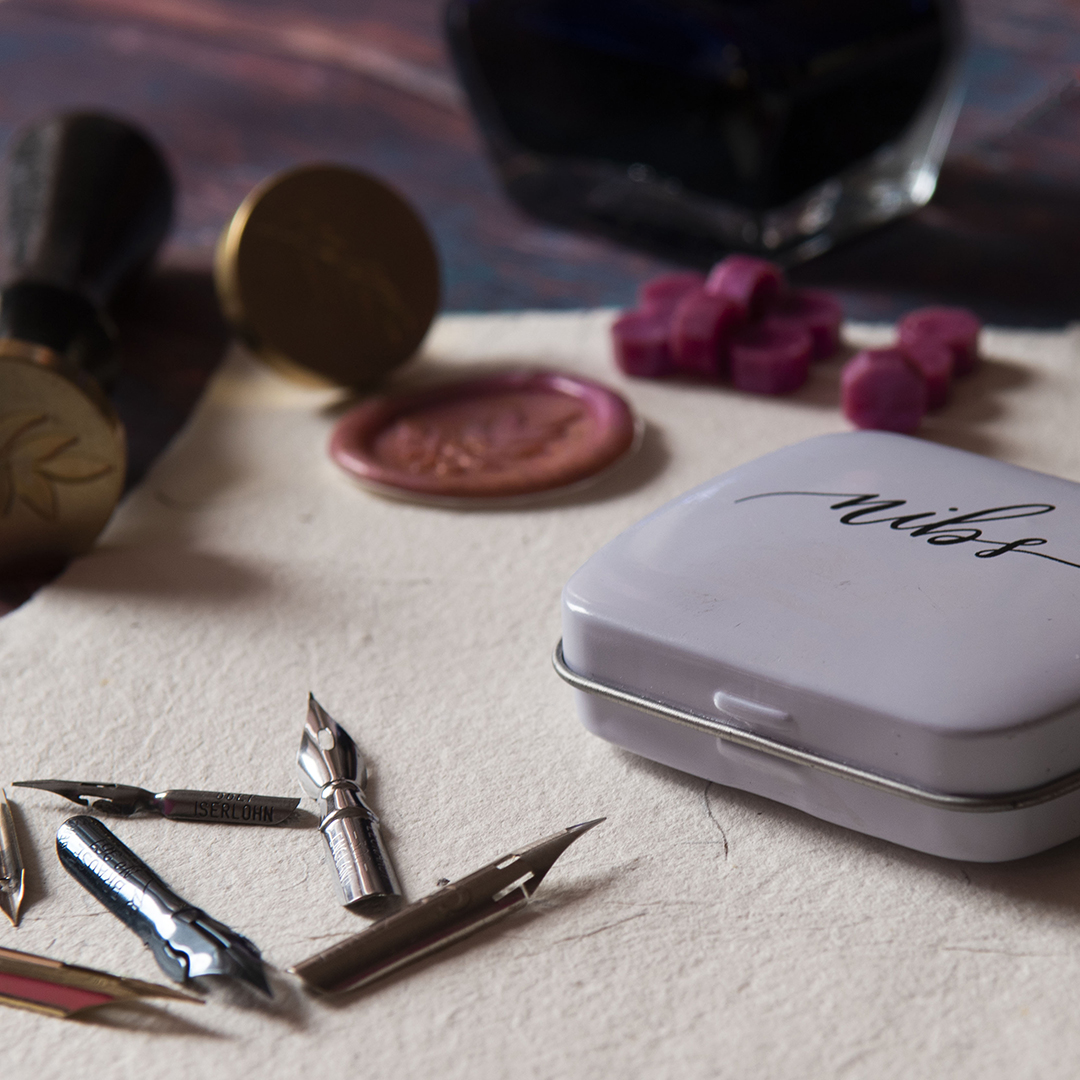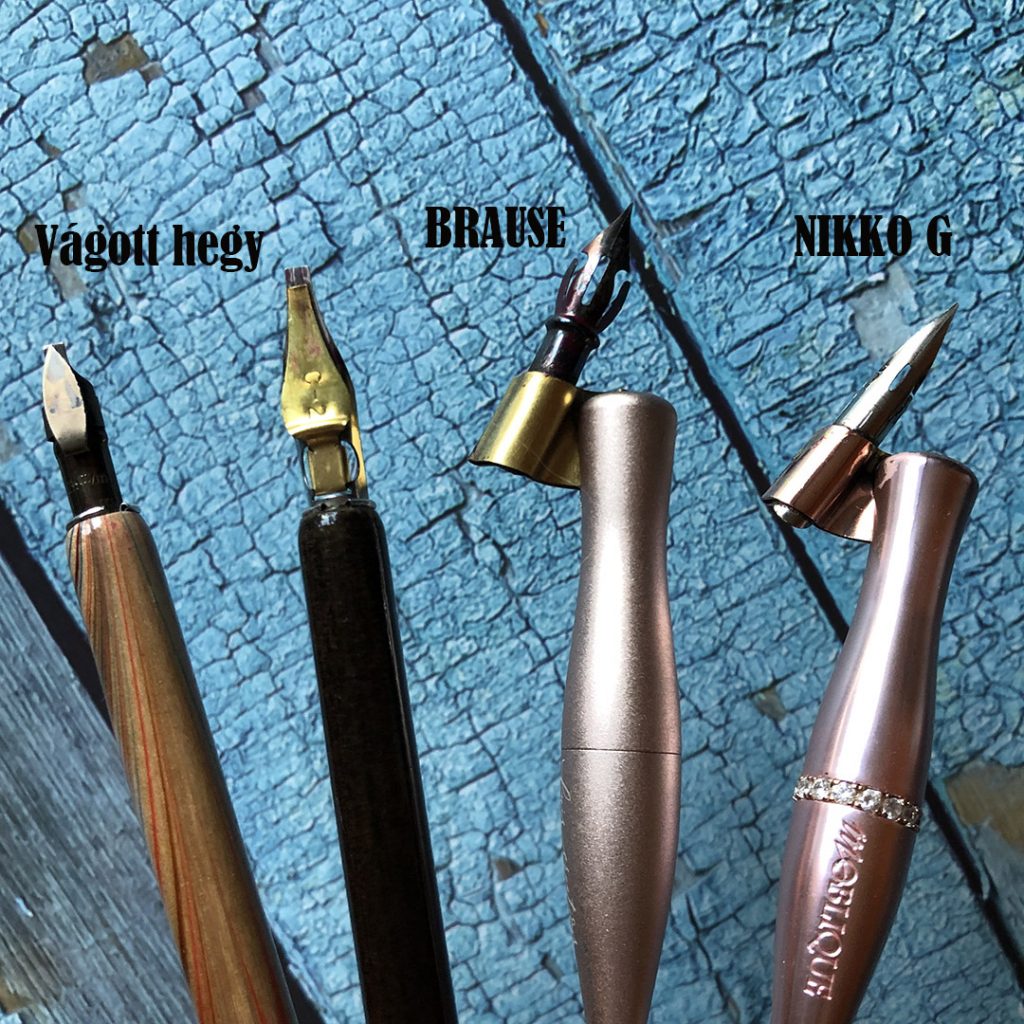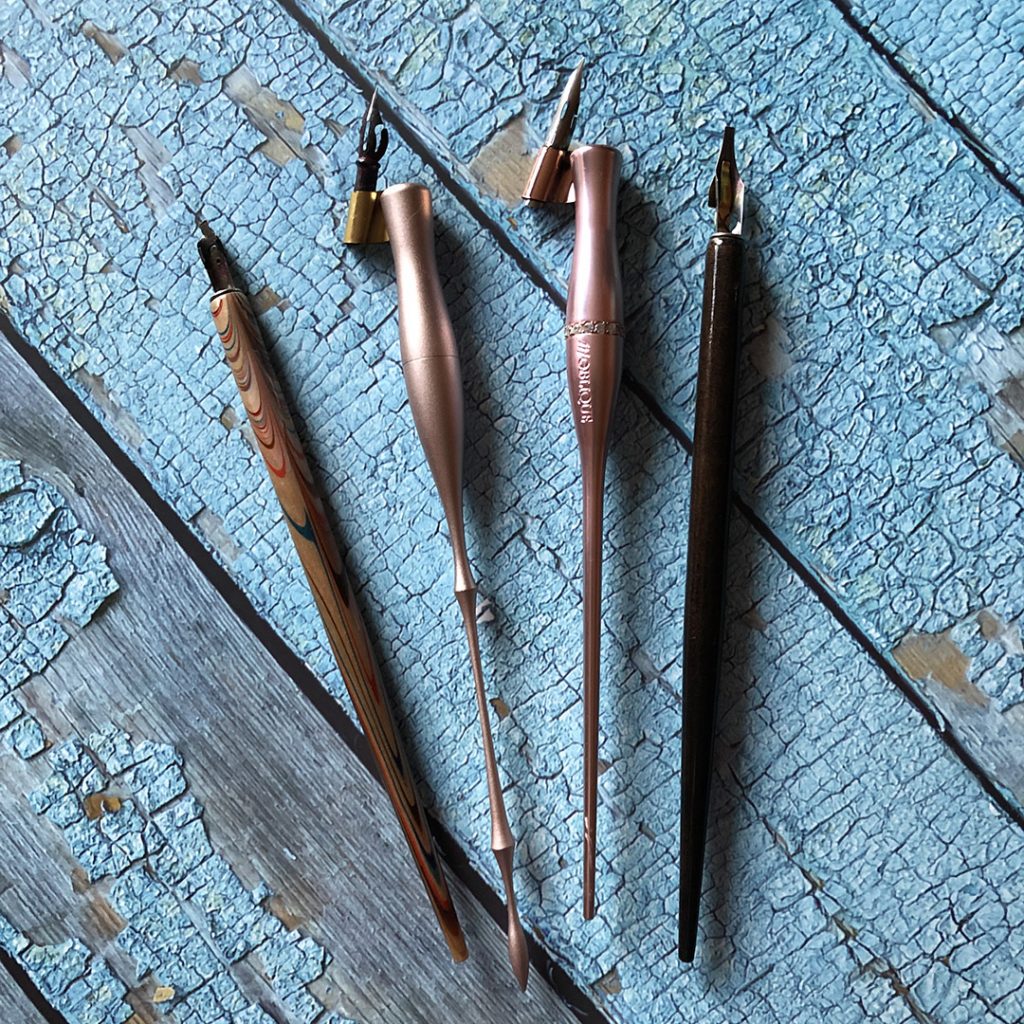
Mártogatós toll kisokos
A kalligráfiai eszközöknél már kicsit érintettem a mártogatós tollat, vágjunk is bele, hogy mire érdemes figyelni az eszköz választásnál.
mártogatós toll
Sokak számára a kalligráfia egyet jelent a mártogatós toll használattal. Azt gondolom, hogy érdemes előbb ecsetfilccel kezdeni, hamarabb jön a sikerélmény, de az is kétségtelen, hogy a tollhegy sercegéséhez semmi sem hasonlítható. Lássuk mit érdemes tudni a mártogatós tollakról.
A tollszár
2 fő csoportja van a mártogatós tollszáraknak az egyenes és ferde tollszár. Kezdésnek mindenképpen az egyenes tollszárat ajánlom, egyrészt ez néhány száz forintért beszerezhető, másrészt ezzel sokkal könnyebb először írni. A ferde tollszárnál elsőre furcsa lehet, hogy a tollhegy ferdén áll, kicsit másképp is kell tartani. Bevallom én viszonylag hamar átálltam a ferde tollszárra, nem nagyon szeretem az egyenest, azonban azt gondolom, hogy ez is attól függ, hogy kinek mi kényelmes.
Azt is meg kell említeni, hogy vannak olyan tollhegyek, amelyek csak egyenes tollszárban használhatóak például a vágott hegyek.
Ha márkát kérdeztek, akkor Moblique a kedvencem, kapható műanyag és fém verzióban is. Bevallom a fém kicsit csalódás volt, bár a súlyát imádom, de sajnos bizonyos tollszemek esetén szétcsúszik.
mártogatós toll – tollszárak
A tollhegy
Elképesztő mennyiségű tollhegy kapható és persze mindegyiknek meg van a maga funkciója. Kezdjük, hogy mi az, amit kezdőknek ajánlanak. Ezek a G-sek, Nikko G, Zebra G. Tachikawa G. Nekem ebből a trióból a Nikko G jött be a legjobban. Azért érdemes ezzel kezdeni, mert elég stramm tollhegy és elég jó a tinta megtartó képessége.
Haladóbb hegyek a Brause „pumpkin” hegye, illetve a Leonradt Principle EF, ezek jóval puhábbak, könnyű szétcsúszni velük, viszont sokkal nagyobb a különbség a vékony és vastag vonalak között, így szerintem elegánsabban lehet velük írni.
Fontos! Minden tollhegyen egy bevonó réteg van, amikor megveszed őket. Ezt enyhe szappanos vízzel tudod eltávolítani egy fogkefe segítségével. Fontos, hogy ezután már ne fogd meg a tollszemet kézzel, csak zsepivel, vagy papírtörlővel, mert a kezünkön lévő természetes zsírréteg beszennyezi, és akkor a tinta nem tud megmaradni benne.
Minden használat után meg kell tisztítani a tollszemet, hogy minél hosszabb életű legyen a tollhegyed. Lehet az előbb említett módszert használni, de elég akár vízzel kiöblíteni, csak mindig töröld át. Néha ezt megteheted fogkrémmel is, csak ne legyen benne bármilyen extra szemcse, mert az megsértheti a tollhegyet.
tollhegyek
A tinta
Rengeteg tinta van a piacon, nekem is rengeteg van. 😅 Általában a sumi tintákat ajánlják kezdésre, és ezzel én is így vagyok. A Kuretake sumi inkje szerintem a legjobb, abból is a fekete tégelyes. Számomra a többi azért nem annyira jó, mert nagyon folynak, és kb. minden betű után mártogatni kell, ami engem megakaszt, és nem tudok flow-ba lenni. A tintáknál előfordulhat, hogy besűrűsödnek, ilyenkor nyugodtan cseppents bele vizet, vagy a tollhegyet mártsd bele vízbe, és máris jobb lesz az állaga.
Tipp: tinta helyett akár használhatsz vízfestéket is, cseppents pár csepp vizet a száraz festékre, majd egy ecset segítségével vidd fel a tollszemre és már használhatod is!
Egyéb eszközök
A papírt azért nem emelem ki, mert megegyezik azzal, amit írtam a kalligráfia eszközöknél, illetve függ a tintától is, szóval ez egy ilyen try & error sztori. Az biztos, hogy a Canson Marker Xl ebben is az egyik legjobb.
Mindenképpen legyen melletted papírtörlő, mert azért minden is előfordulhat, meglökheted a tintatartót, kicsit mélyebbre mártod a tollat és minden tintás lesz stb., szóval életmentő lehet. 🙂 Persze ez is majd javul a gyakorlás során. Emlékszem az elején gyakorlatilag befedtem mindent papírtörlővel, ma már csak egyet tartok magam mellett.